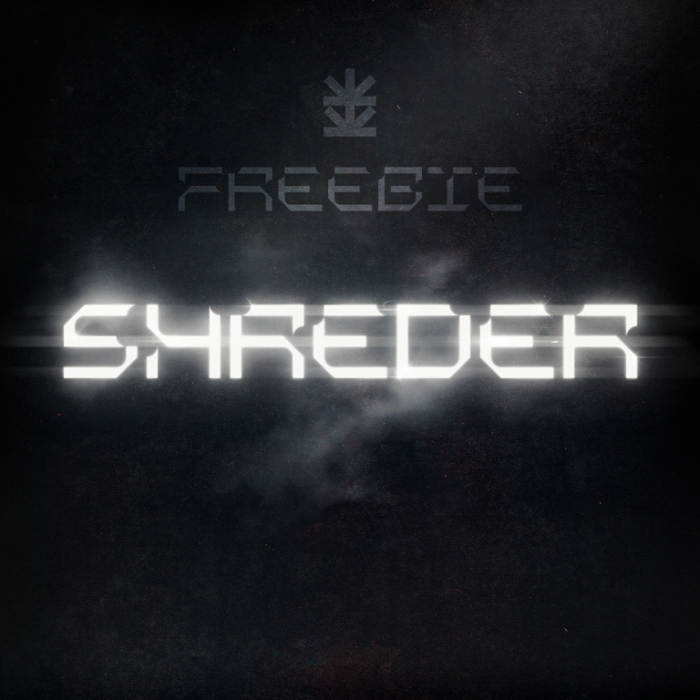
Привет. Отличный шрифт. Но Кирилица плохо читается, из-за букв Д З Ц Щ Ю Ъ. З стоит сделать как В, а Л Д Ц Щ Ъ должны выходить выносными элементами за рамки квадрата (как ф), на то это и выносные элементы.
Добротное замечание. Стоит учесть в последующей версии этого шрифта. Буквы Х и Ш так же следует обдумать как следует. Про Д и Ю я молчу :D. Что тут сказать? С Кириллицей работать непросто. А в работе подобного формата подавно.